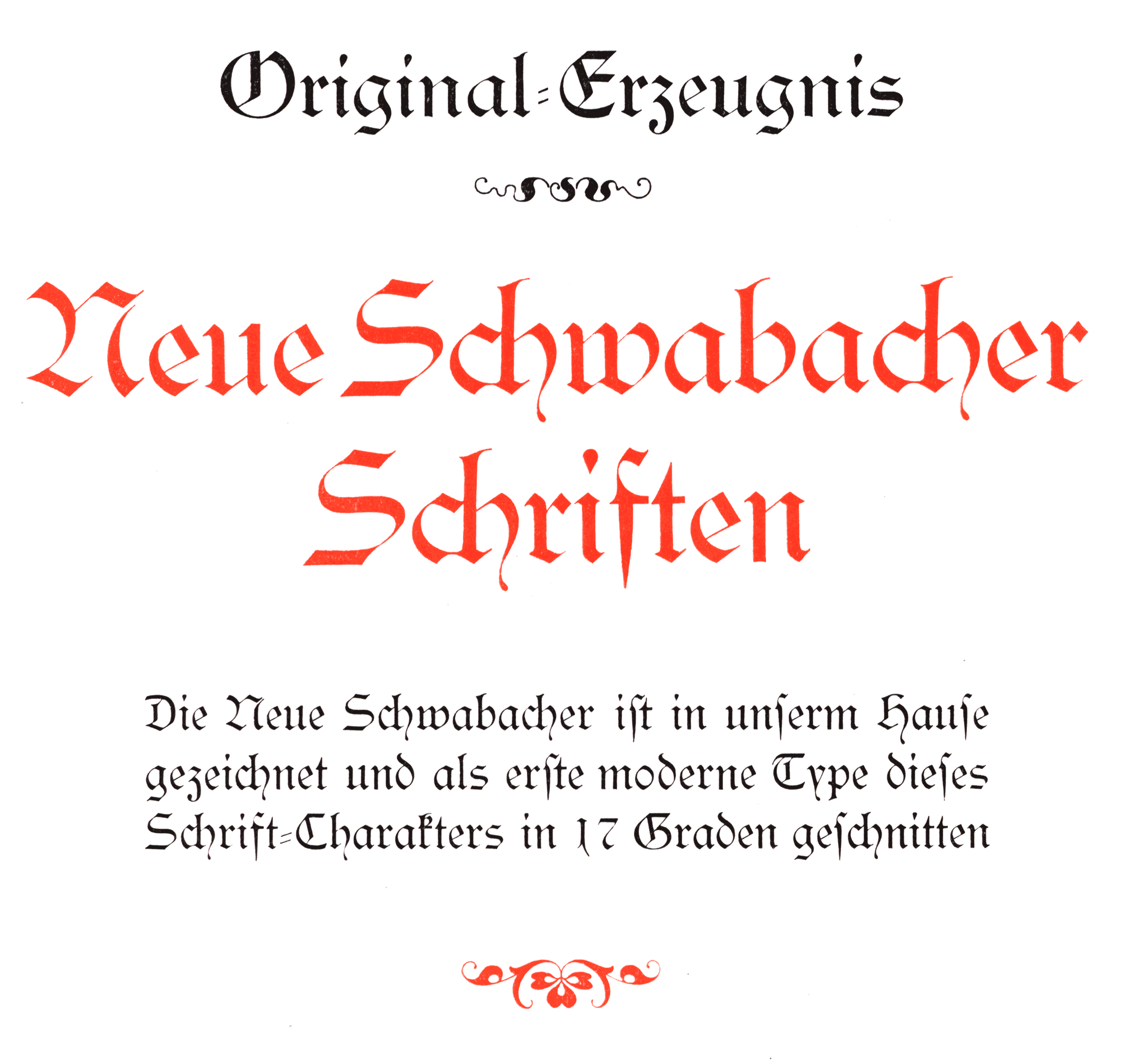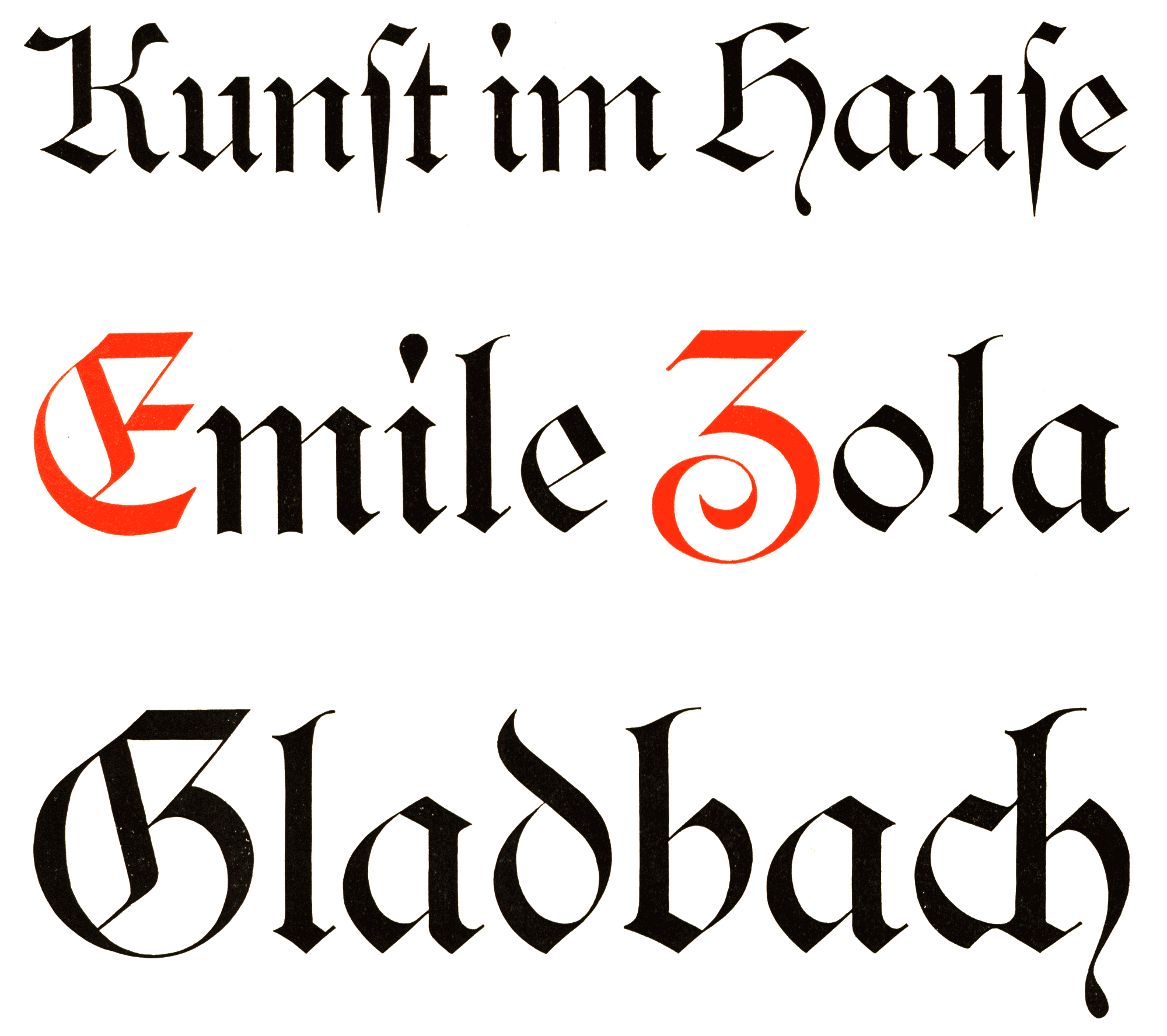
Font-Wiki: Neue Schwabacher
Diese Schwabacherschrift von Albert Anklam erschien 1976 bei der Hamburger Gießerei Genzsch & Heyse. Sie wurde jedoch auch unter gleichen oder anderen Namen bei vielen anderen Gießereien angeboten.
Eine kostenlose Digitalisierung gibt es unter dem Namen Yonkers. Gerhard Helzl hat drei Schnitte im Programm und von RMU Fonts gibt es ebenfalls eine kommerzielle Digitalisierung.